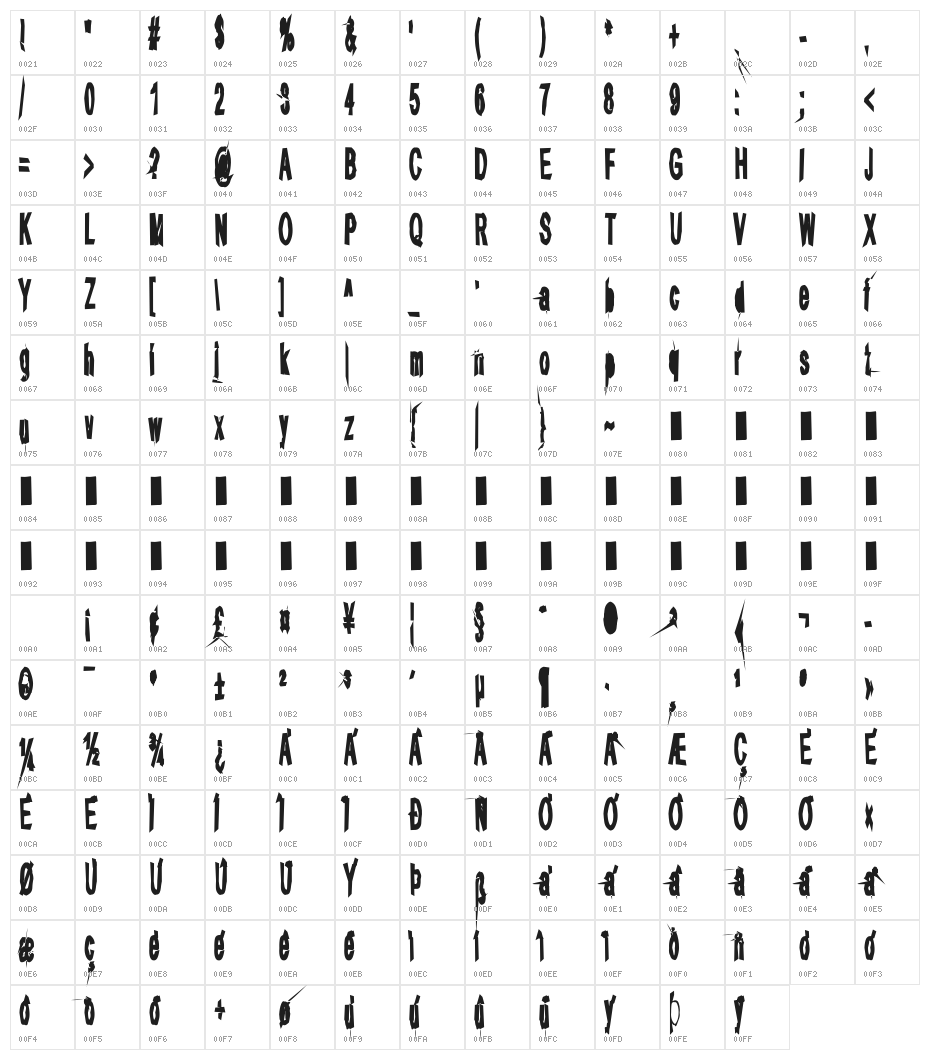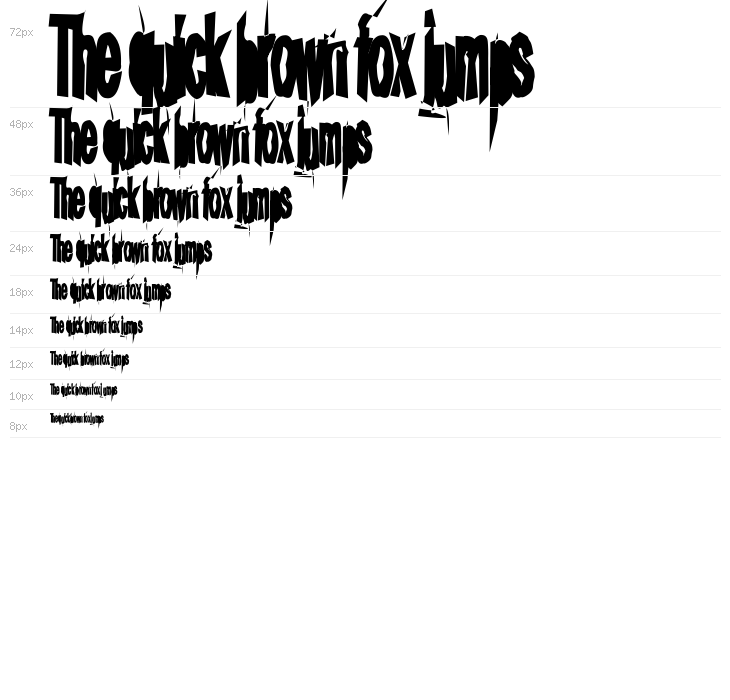
aRape Angular Font
| Gesamtstil | Modern, Edgy |
| Vorgeschlagene Projekte | Ideal for urban-themed posters, edgy branding, album covers, or any project requiring a bold, rebellious aesthetic. |